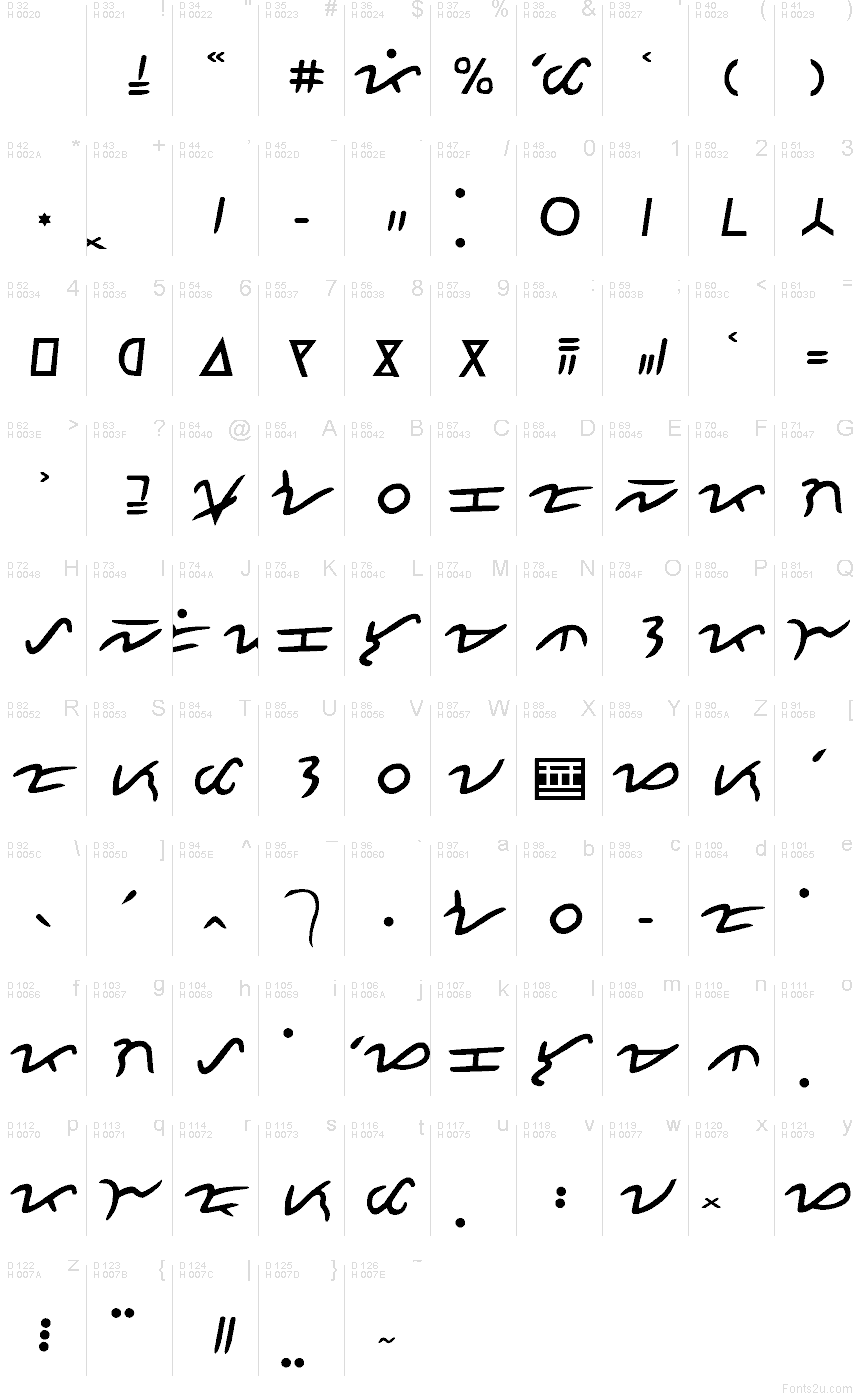
DATU-16 de Apulakan Siklab é uma fonte de símbolos gratuita desenhada a pincel, com traços amplos e fluidos e um acabamento nitidamente artesanal. A variação na espessura dos traços, as curvas em gancho e os arcos arredondados dão às formas o aspeto de carateres feitos rapidamente com tinta, mantendo cada símbolo uma silhueta compacta e deliberada.
A embalagem pode utilizar estas formas caligráficas como emblemas recorrentes, selos ou marcas decorativas, particularmente para artigos artesanais e produtos feitos à mão. Também se adequam a cartazes, merchandising e gráficos digitais com temas folclóricos ou cerimoniais, onde os símbolos se tornam parte da composição artística em vez de texto comum. O seu papel mais evidente é o de um conjunto de marcas gráficas expressivas para branding ilustrado.